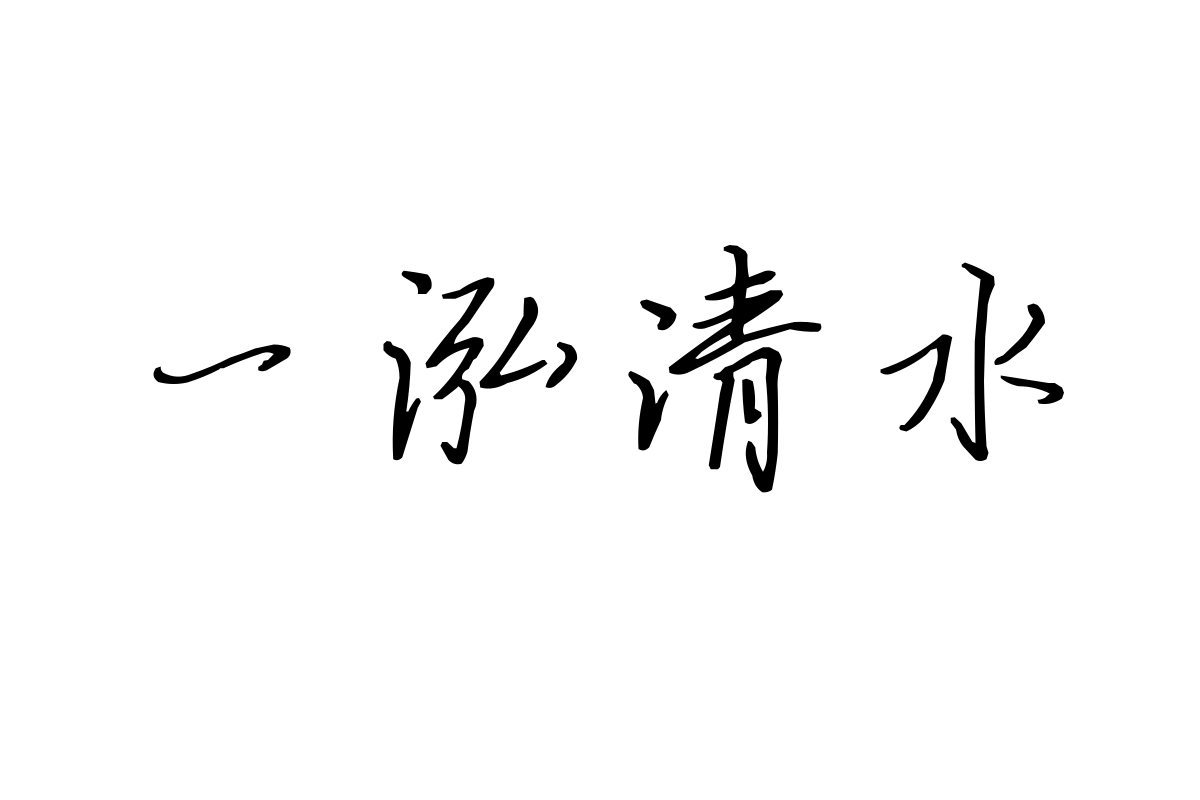
汉仪寒石体简是一套专为中文字体设计的字体,它以其独特的风格和设计特点,在视觉上给人以清新、简洁的感觉。
该字体采用了现代的设计手法,将传统书法的韵味与现代审美相结合,形成了一种独特的艺术风格。它的线条流畅而有力,结构紧凑而富有张力,给人一种强烈的视觉冲击力。
在字形设计上,汉仪寒石体简注重细节的处理,每个笔画都经过精心雕琢,使其既有力度又不失柔美。同时,该字体还巧妙地运用了不同粗细的线条,使得整体效果更加丰富多样。
此外,汉仪寒石体简还具有一定的可读性,无论是在日常书写还是用于印刷品中,都能保证清晰易读。因此,它不仅适合作为装饰字体使用,也非常适合用于正式场合的文本展示。
总的来说,汉仪寒石体简是一款具有独特魅力的中文字体,它以其独特的设计风格和良好的可读性,赢得了广泛的赞誉和喜爱。